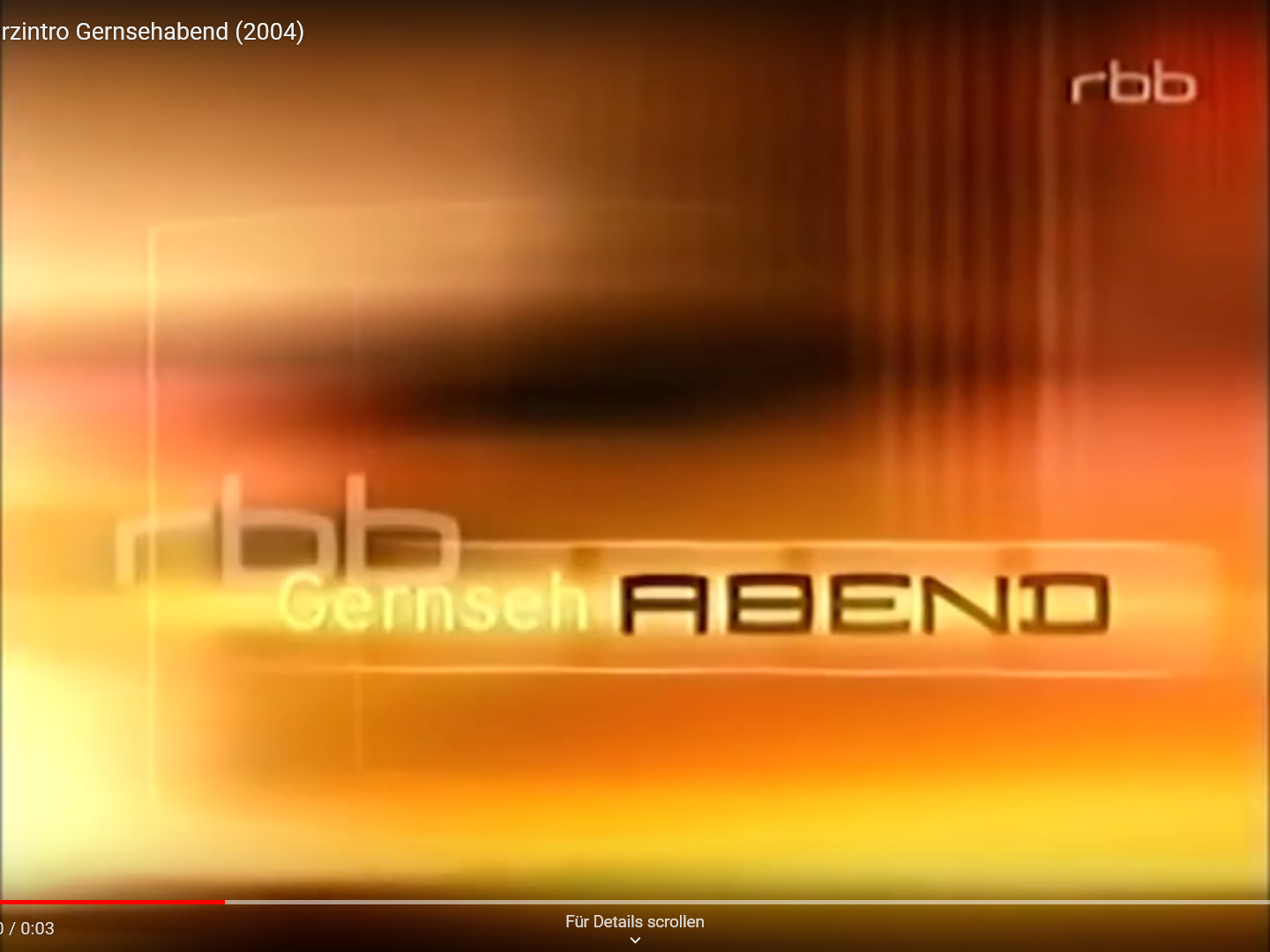
TV Sender rbb Schriftart gesucht (Gernsehabend)
ich bin auf der Suche nach der Schriftart, die das Wort ABEND zeigt. Meines Erachtens wurde diese bzw ähnlich auch bei dem Firmenlogo "EL/SI" verwendet. Es unterscheidet sich jedoch das "E".
Kann jemand "sachdienliche" Hinweise zur Ergreifung des Schriftartennamens machen?
Ich vermute eher, dass die wenigen Buchstaben im Stil des rbb-Logos gestaltet wurden und kein kompletter Font existiert, so wie ich es bei "aktuell" ebenfalls vermute.
Da ich vermute, da die Firmal EL-SI (Landsberger Str 131, Berlin) auch Werbung in dieser Schrift am Gebäude hat, dass es einen Schriftsatz gibt. Ich gebe noch nicht auf.
Bei der Agentur mal anfragen? GUD.berlin hat den RBB von 2017 bis 2021 betreut.
Die Grundform der Buchstaben hat 2003 DMC erstellt, der Schriftzug "Abend" ist ja aus den Ursprungsjahren.
DMC (ich glaub damals Hamburg, gibts nicht mehr), schreib ich als nächstes an. Ich hab das Design Team des rbb angeschrieben und GUD.